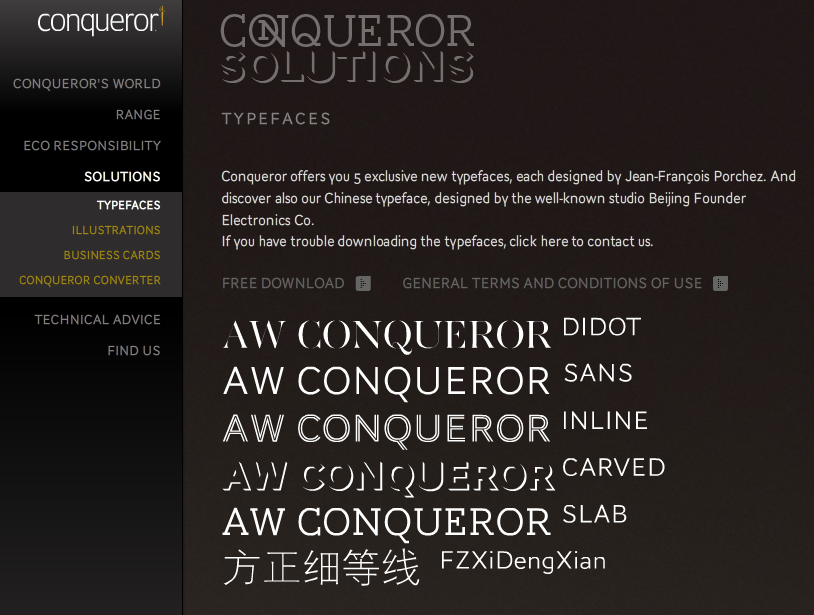
AW Conqueror for free
Jean François Porchez was approached at the end of 2009 by Reflex Image to create a set of typefaces to relaunch the Conqueror papers collection. An important website and various others communications material was created by the agency. The designer Seb Lester and the photographer Thomas Brown have been hired to created various visuals using Conqueror fonts.
For the first showing to the agency, we’ve created a set of fake in use pieces using the AW Conqueror fonts (at the time with a very small glyph set who explain some fake texts). The idea was to recreate a 60-70’s ambiance to clearly the set the general feeling of the typeface family.
Launched at the end of August 2010 by Arjowiggins, AW Conqueror is a family of Free fonts available at Conqueror.com website. This family include 5 variations with great potential: Small glyph sets, mostly all caps, but based on same structure, with some connection between them (width for example), to offer a great & easy titling toolbox to any designers, from skillful to beginner.
Vielleicht sollte erwähnt werden, dass es sich um Crippleware handelt, wie der Angelsachse so schön sagt. So zwei-drei Dutzend Glyphen enthalten statt des zu erwartenden Zeichens den hochgestellten Schriftzug »PTF«. Das betrifft z.B. <>{}¥¢©®¹ (und alle anderen hochgestellten) und ½ (und alle anderen Brüche). Bei den Headline-Schriften ist das sicher weniger dramatisch, aber die Didot, Sans und Slab haben dasselbe Problem.
Nee, die wurde ja nicht absichtlich kastriert sondern einfach nicht weit genug ausgebaut eben weil sie nur für Display-Anwendungen herhalten muß/soll. Steht ja auch eindeutig im Begleittext. :tutor:
Sicher, keine Schrift ist komplett ausgebaut. Aber wenn anstelle eines fehlenden Glyphen ein Logo eingebaut wird (und das auch gleich noch einige Dutzend mal), dann versucht der Schriftgestalter doch wohl schon, eine Botschaft zu senden.
Naja, wenn’s außergewöhnliche Glyphen sind, kann man’s ja noch verstehen. Aber bei gängigen wie »§« oder »°« ist es schon nervig.
Meine Güte, das ist wie bei jedem anderen Free-Font auch! Man benutzt ihn dann eben nur für Anwendungen bei denen er sich einsetzen läßt. Oder kauft sich halt was besseres. Trotzdem kann man damit tolle Sachen machen. :x
Auch wenn die Schrift-Autoren (bzw. Verfasser des Werbetextes) sich vielleicht damit heraus reden können, dass sich das explizit nur auf das Lizenzmodell und nicht notwendigerweise auf die professionelle Qualität der Schriften bezieht, kann doch zumindest der Eindruck entstehen, hier würden Schriften professioneller Qualität angeboten, nur eben für eine gewisse Zeit für 0€. Schlimmstenfalls schlussfolgert der potentielle Kunde, dass der Anbieter Schriften ohne <>, §, ¥, ¹ für professionell ausgebaut hält.
Wären die Schriften von vornherein als »normale« Freefonts (mit Abstrichen, nur zum Anfüttern) deklariert worden, wär das ne ganz andere Geschichte. Aber die oben zitierten Formulierungen (»professional«, »for any project«, »only difference … you don’t have to pa[y]«) suggeriert eben anderes?—?und das kann für den professionellen Ruf des Anbieters nicht gut sein.
Ach das ist doch einfach Mumpitz, es steht eindeutig da daß die Fonts für ein mock-up generiert worden sind und einen deutlich eingeschränkten Zeichenumfang haben. Wenn Du da unbedingt einen hohen professionellen Anspruch reininterpretieren willst, dann ist das Dein Privatvergnügen. Es steht aber einfach da daß dem nicht so ist. Außerdem ist sogar noch extra ausgeführt, daß Du Dich, wenn Du nicht zufrieden bist und Extra-Wünsche hast, einfach an die Foundry wenden kannst. :blabla:
Die Carved sind die einzigen die ich benutzen würde. Und bei denen als Headline-Schriften ist das Fehlern dieser Glyphen nicht so problematisch. Didot, Sans und Slab würde ich eher ersetzen. Für die Sans könnte man folgende freie Schriften ins Auge fassen: